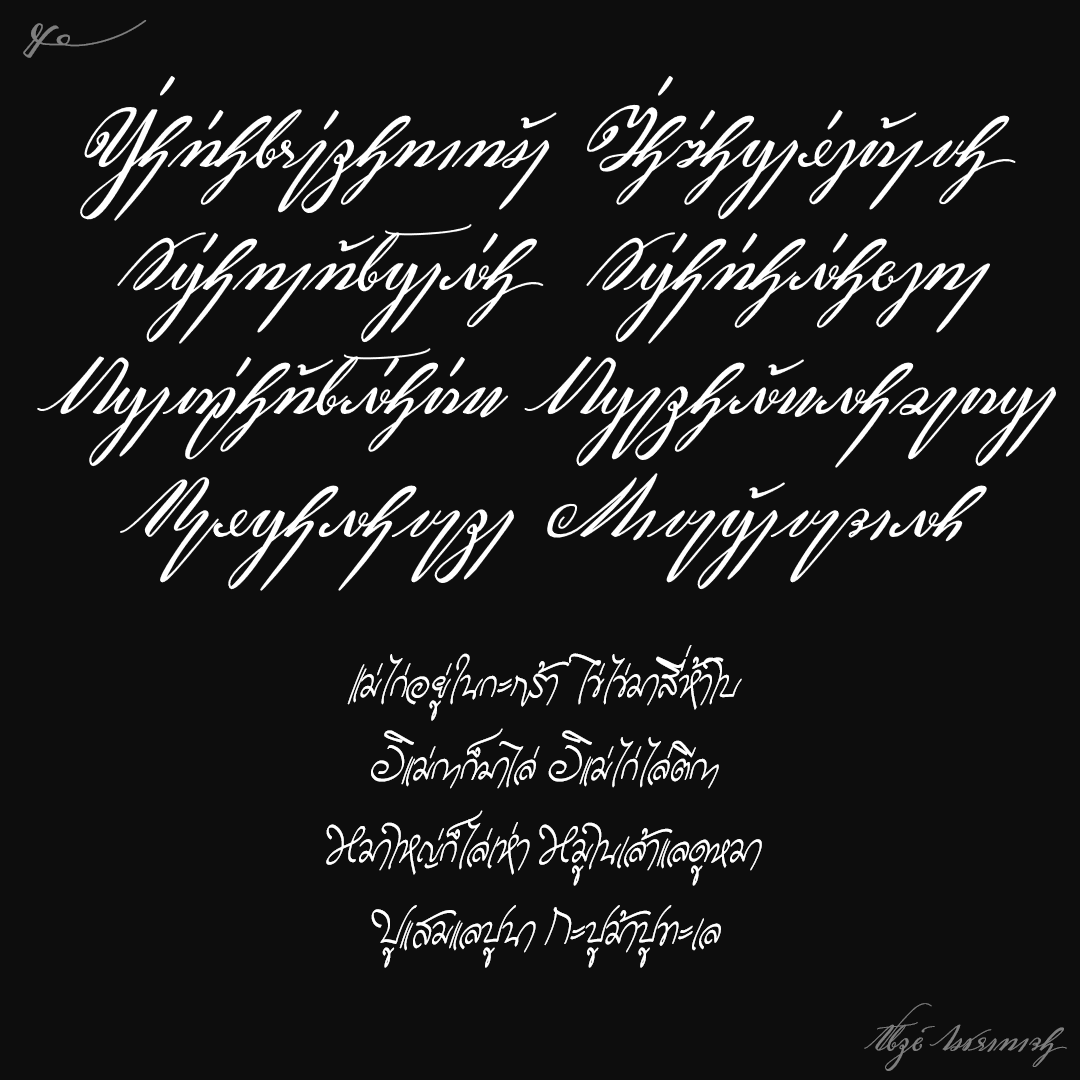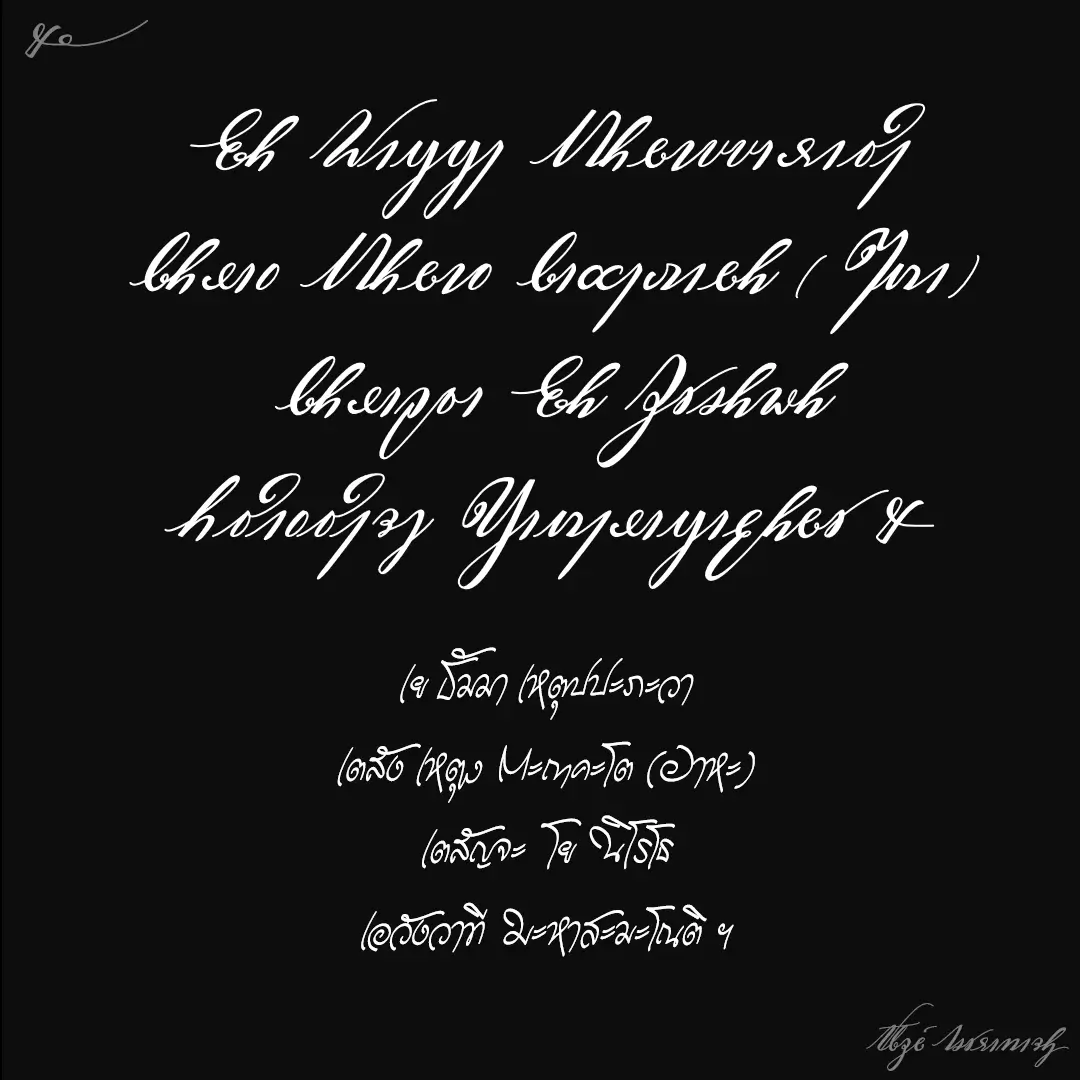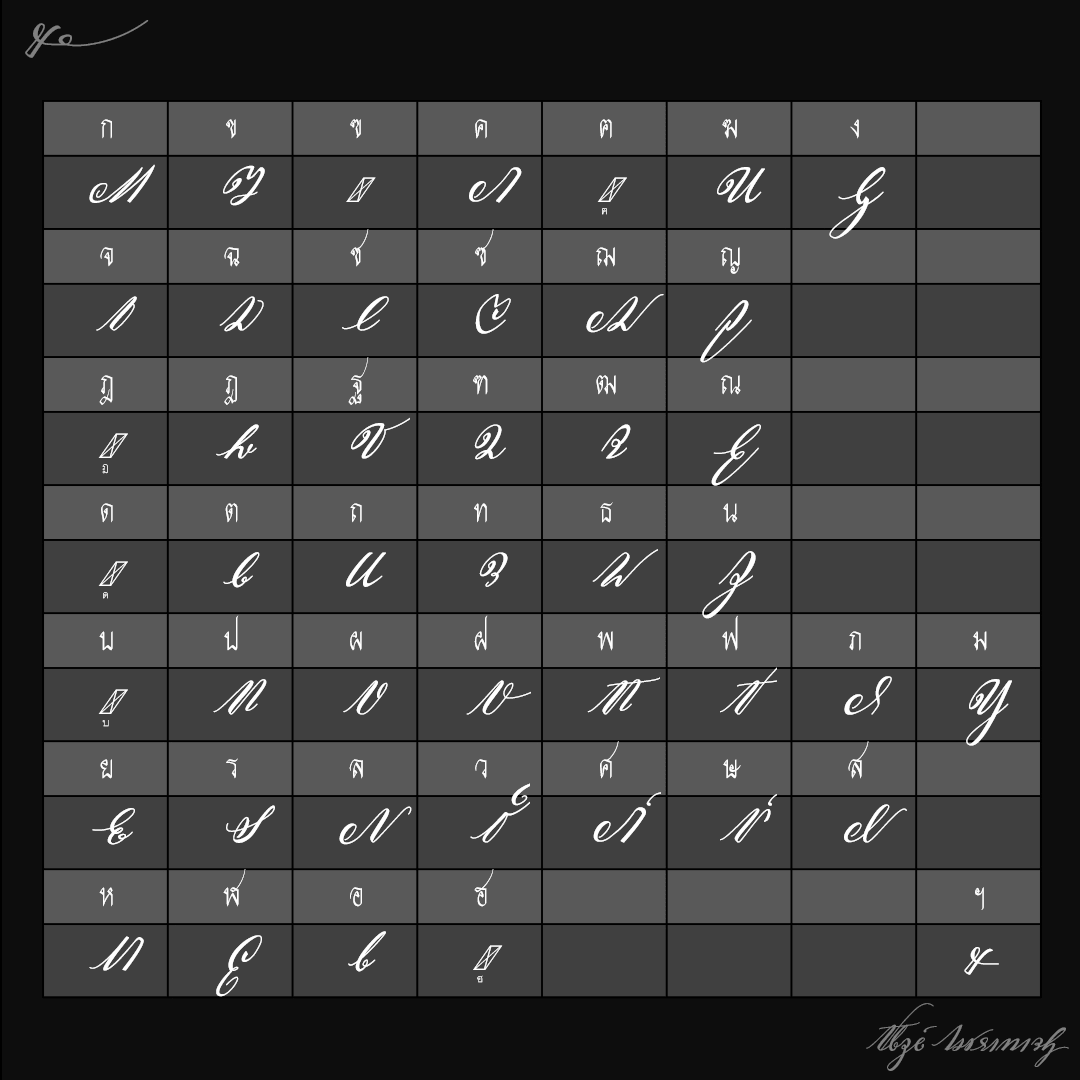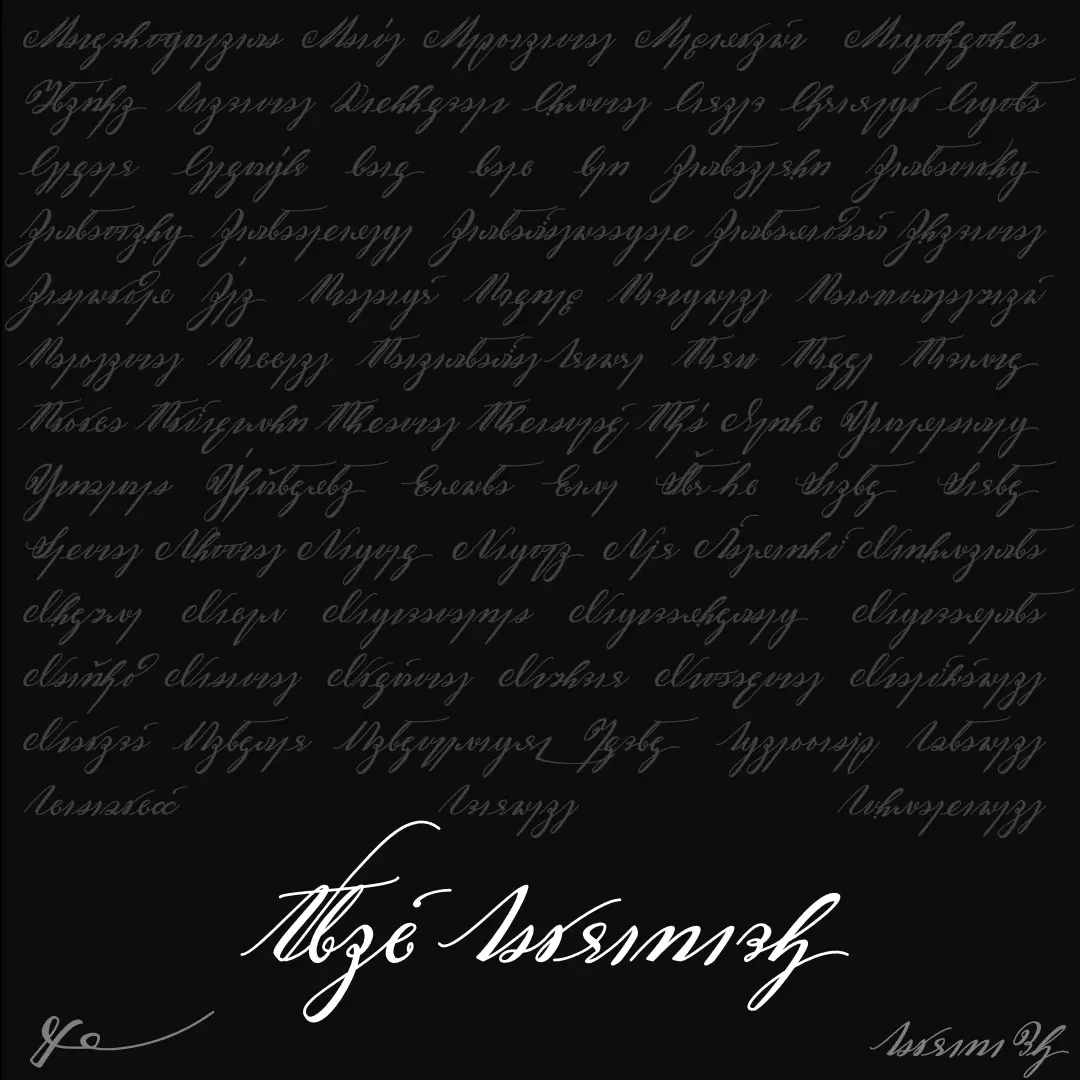
ฟอนต์อักษรอริยกะตัวเขียน ใช้ได้ทั้งภาษาไทย และภาษาบาลี ..ต่างจากอักษรปัจจุบันทั้งรูปอักษร วิธีพิมพ์ แนะนำให้ดูคู่มือก่อนใช้งาน
แถม : ฟอนต์อริยกะปาฬิ (AriyakaPL) สำหรับบาลีตัวเขียนโดยเฉพาะ..พิมพ์แบบไทยพินทุ
อริยกะไท (SOV_AriyakaTH)